Какие бывают брусковые шрифты и чем различаются их конструкции
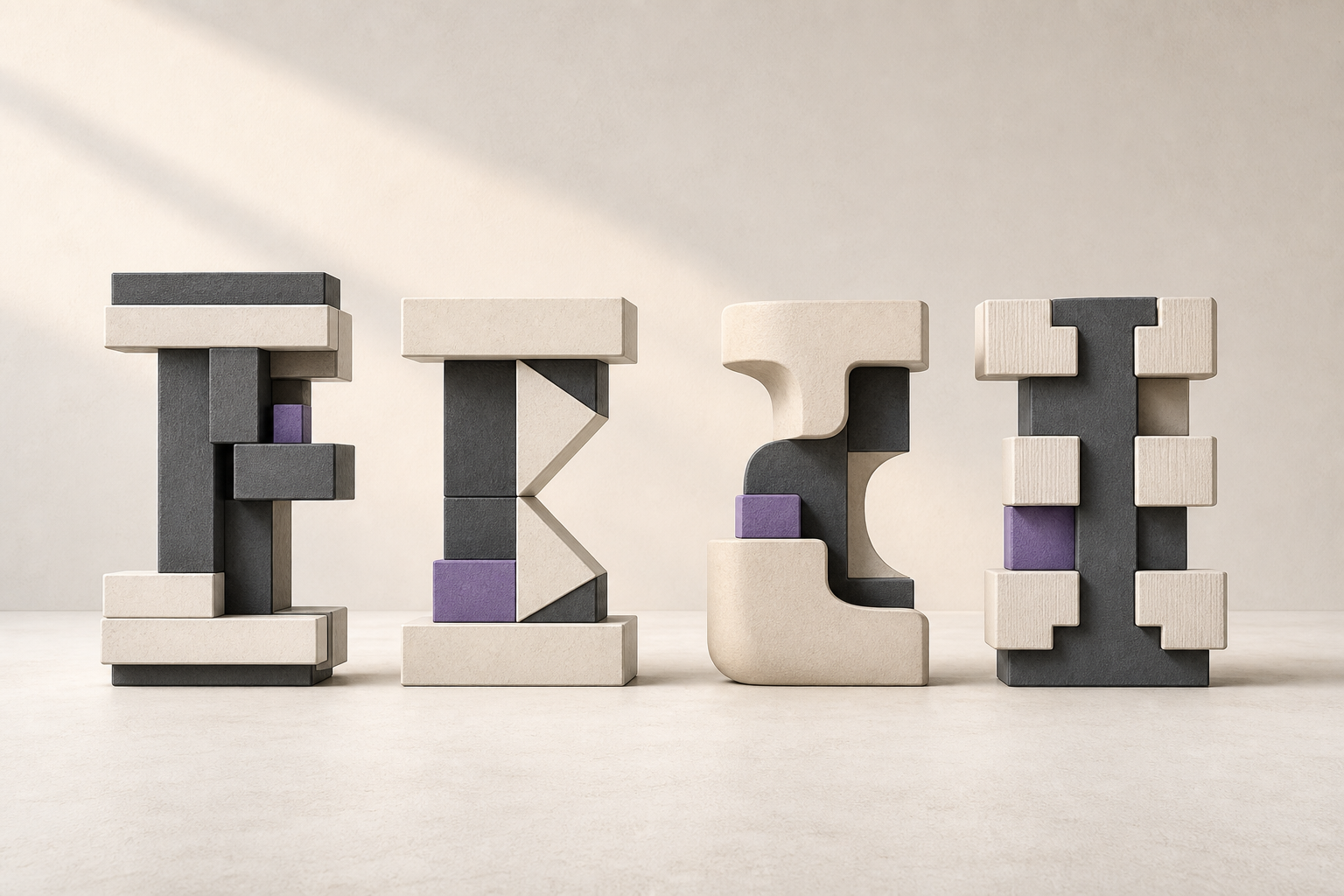
Какие бывают брусковые шрифты и чем различаются их конструкции
Брусковые шрифты — это шрифты с массивными, обычно прямоугольными засечками, которые заметно влияют на силуэт букв и общий ритм набора. Их конструкции различаются контрастом штрихов, формой примыкания засечек, шириной знаков, характером окончаний и степенью геометричности. Ниже разберём основные разновидности и правила выбора для логотипов, заголовков, упаковки и текста.
Что такое брусковый шрифт
Брусковый шрифт, или slab serif, относится к шрифтам с засечками. Его главный признак — крупная засечка, напоминающая небольшой брусок: она может быть горизонтальной, почти прямоугольной, с плавным переходом к основному штриху или присоединяться резко, без скругления. В отличие от антиквы, где засечки часто тонкие и поддерживают модуляцию пера, в брусковых гарнитурах засечка становится самостоятельным конструктивным элементом.
Название «египетские» исторически применяли к ранним шрифтам этого направления, но сегодня понятия не полностью совпадают. Брусковая группа шире: в неё входят монолинейные геометрические гарнитуры, машинописные шрифты, гуманистические варианты и конструкции с заметным контрастом. Поэтому при выборе важно смотреть не только на наличие засечек, но и на устройство всего алфавита.
Главные признаки конструкции брусковых шрифтов
Конструкция шрифта — это не декоративный эффект, а система взаимосвязанных решений. Одинаково прямоугольные засечки могут создавать строгий промышленный образ или мягкую редакционную интонацию в зависимости от пропорций, толщины штрихов и формы внутренних просветов. Для анализа полезно рассматривать несколько параметров одновременно.
- Форма засечек показывает, имеют ли они скруглённое примыкание, острый угол или резкий переход.
- Контраст определяет разницу между тонкими и толстыми штрихами.
- Пропорции влияют на ширину букв, плотность строки и характер заголовка.
- Ось округлых знаков задаёт направление кажущегося движения в буквах О, С и Э.
- Апертуры определяют, насколько открыты внутренние части букв и как они читаются в малом размере.
- Окончания штрихов формируют настроение: они могут быть прямыми, скошенными, округлыми или клиновидными.
- Межбуквенное пространство задаёт ритм и часто сильнее влияет на впечатление, чем отдельная буква.
Основные разновидности брусковых шрифтов
Классические египетские шрифты
Классические египетские гарнитуры строятся на плотных вертикальных и горизонтальных штрихах, крупных засечках и сравнительно простом рисунке. Их формы часто выглядят тяжёлыми, уверенными и плакатными. Контраст обычно невысокий, поэтому буквы сохраняют цельность на вывеске, этикетке или обложке. При этом ранние образцы могут казаться грубее и плотнее современных интерпретаций.
Такой шрифт уместен там, где нужно передать основательность и физическую выразительность: для названия мастерской, упаковки инструмента, афиши, заголовка исторического или индустриального проекта. В длинном тексте чрезмерно тяжёлый вариант быстро создаёт серый и перегруженный набор, поэтому его чаще используют в коротких фрагментах.
Геометрические монолинейные конструкции
Геометрический брусковый шрифт стремится к простым формам: кругам, прямоугольникам и прямым линиям. Толщина штрихов у него может быть почти одинаковой, а засечки — симметричными и чёткими. Буквы выглядят собранно и рационально, но при слишком механическом построении кириллица может потерять естественный ритм. Особенно внимательно нужно проверять Д, Ж, К, Л, У и фрагменты с диагоналями.
Геометрические варианты хорошо работают в айдентике, навигации, заголовках цифровых продуктов и современной упаковке. Они поддерживают ощущение порядка, технологичности и ясной структуры. Для небольшого кегля лучше выбирать конструкцию с увеличенной высотой строчных, умеренной плотностью и достаточно открытыми просветами.
Машинописные и моноширинные брусковые шрифты
Машинописные гарнитуры наследуют характер печатных машин: знаки часто имеют фиксированную ширину, заметные засечки и неодинаковую визуальную плотность. Моноширинность означает, что каждый знак занимает одинаковое горизонтальное пространство, хотя сами буквы могут быть разной фактической ширины. Это создаёт узнаваемый технический ритм и напоминает о коде, документах и архивной печати.
Моноширинный брусковый шрифт удобен для фрагментов кода, таблиц, технических подписей, концепций в эстетике ретро и проектов, связанных с инженерией. Для обычного рекламного текста он часто слишком разрежен или неэкономичен по ширине. Если нужен только визуальный намёк на печатную машинку, лучше использовать пропорциональный шрифт с характерными засечками, а не жертвовать удобством набора.
Гуманистические брусковые гарнитуры
Гуманистическая конструкция сохраняет брусковые засечки, но смягчает геометрию признаками рукописного или каллиграфического происхождения. В ней заметнее различия толщины штрихов, живее форма округлых знаков, а окончания могут быть слегка скошенными. Такие гарнитуры обычно воспринимаются теплее и лучше поддерживают длительное чтение, если их рисунок не слишком декоративен.
Брусковые шрифты объединяет массивная засечка, но их конструкции заметно различаются: от тяжёлых египетских и строгих геометрических до гуманистических, машинописных и контрастных. Выбирайте гарнитуру по задаче, тестируйте кириллицу и оценивайте не отдельную букву, а весь ритм текста.